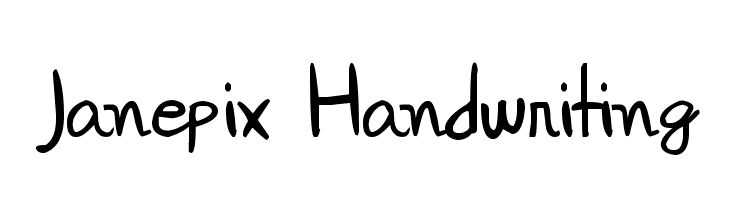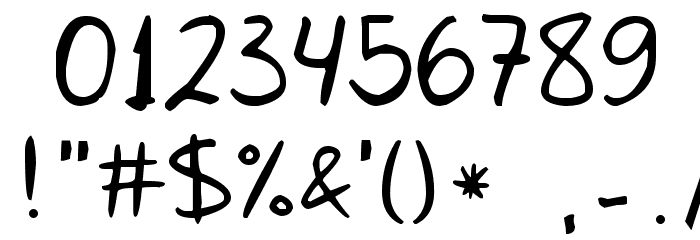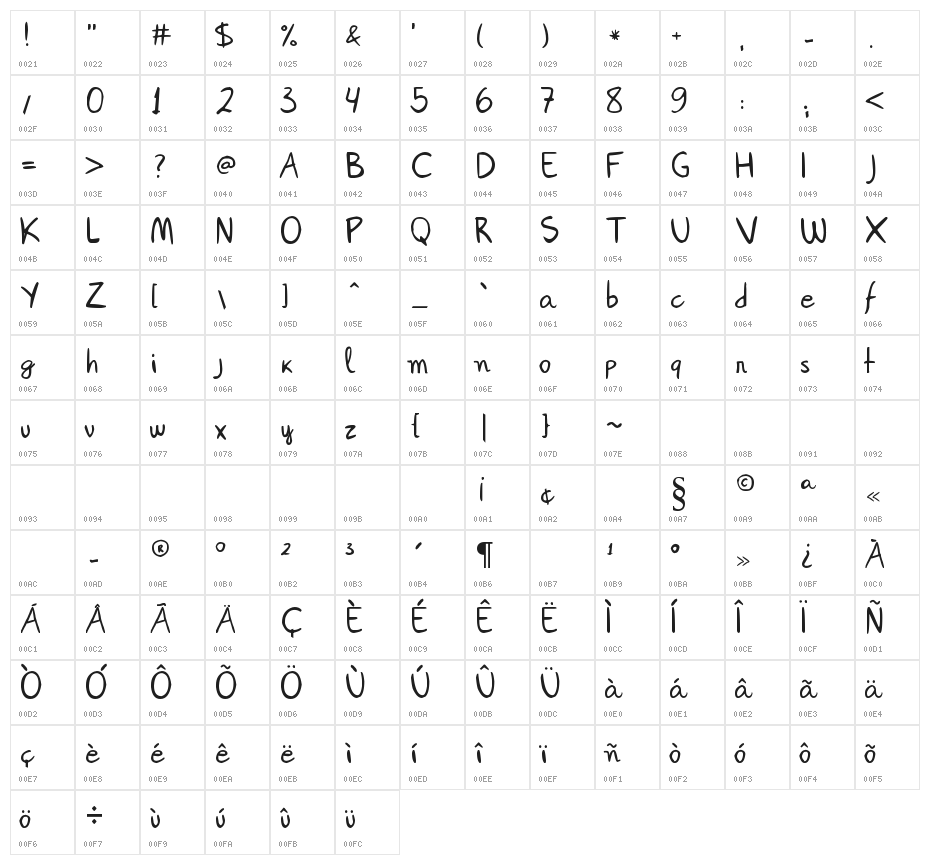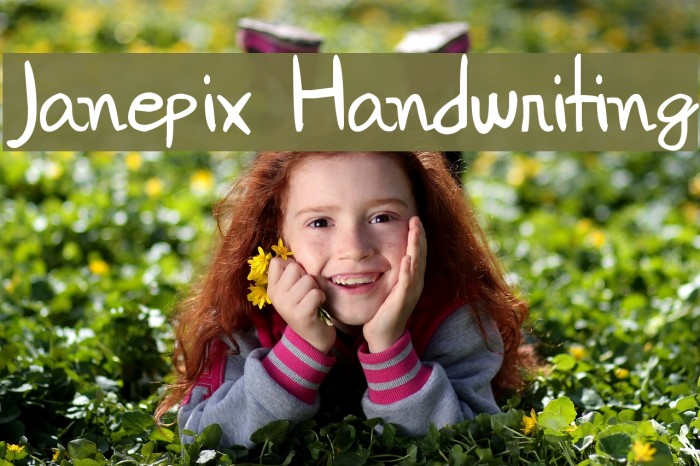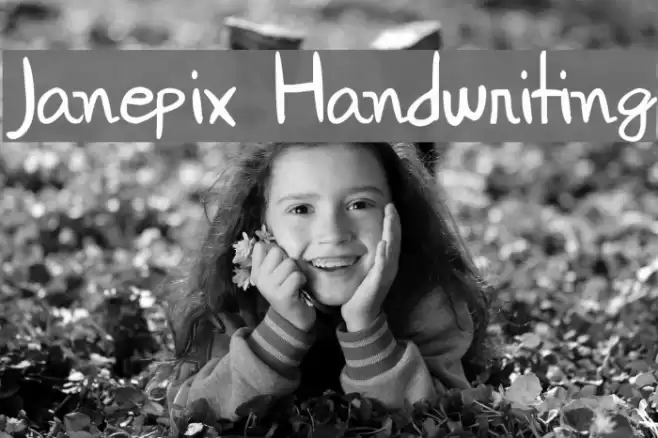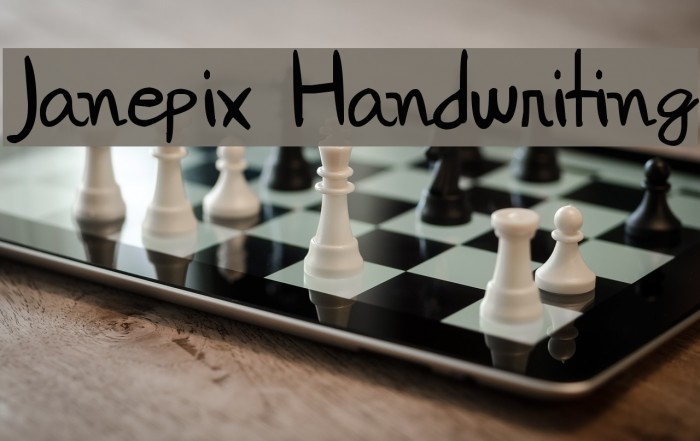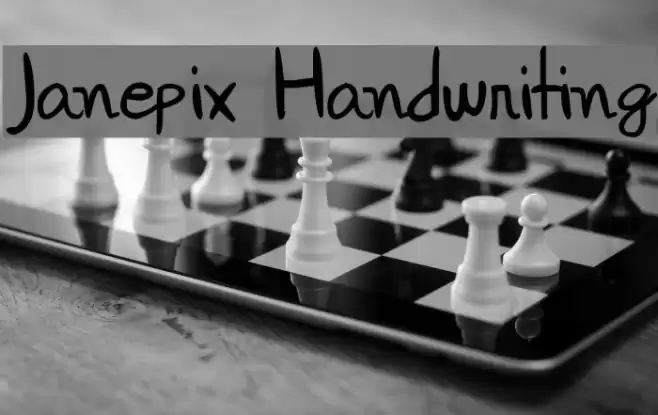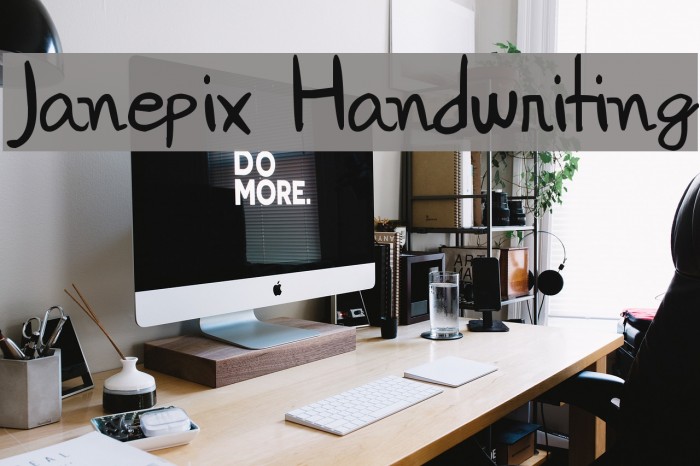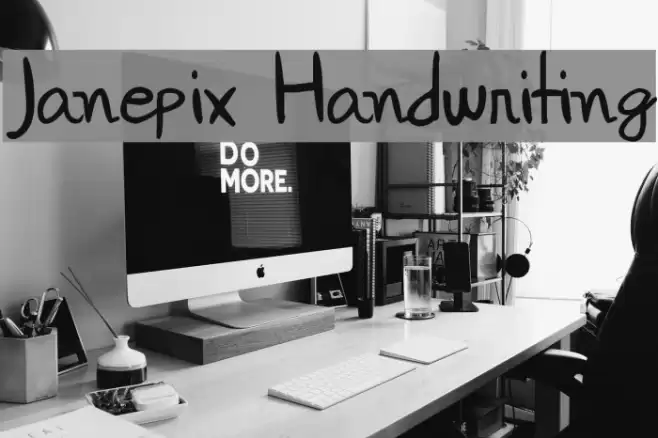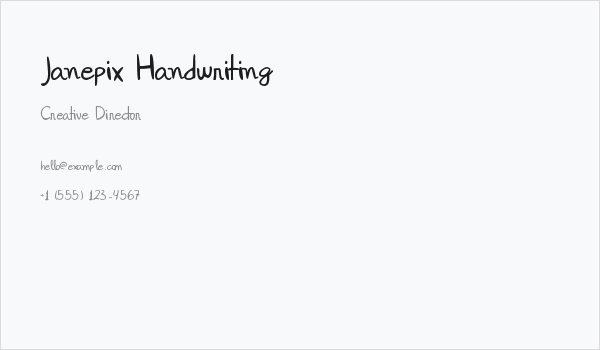
Janepix Handwriting Font
| Общий стиль | Casual |
| Область применения | Headlines, Informal text, Personal projects |
| Рекомендуемые проекты | Ideal for greeting cards, personal blogs, children's books, and informal branding projects. |